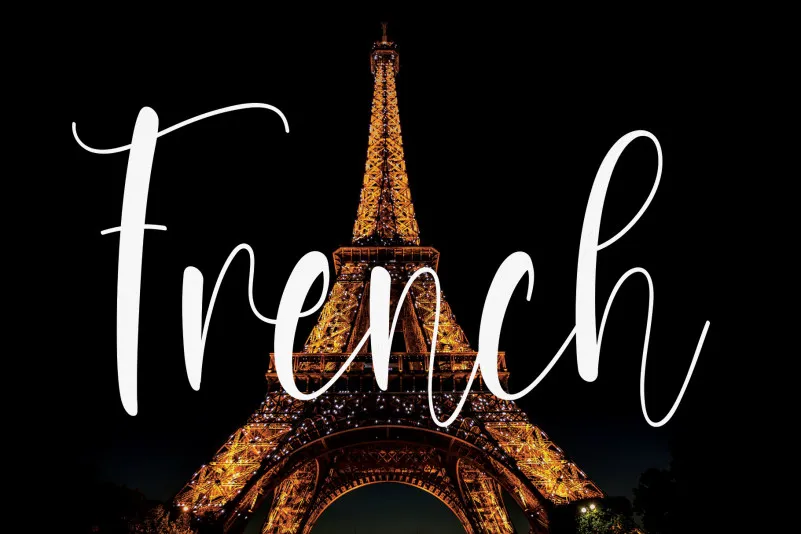
Farmwork Font – Download Grátis
Aqui está uma descrição em português para a página de download da font ‘Farmwork Font’, focando nas características do tipo de letra escrita à mão: Esta é uma fonte escrita à mão especial e criativa, com caracteres elegantes que impressionam com seu estilo! Use esta linda tipografia para adicionar um toque encantador a rótulos, designs de produtos, marcas d’água, fotografias e muito mais. Através da Farmwork Font, você pode enriquecer o design visual de qualquer projeto, tornando-o ainda mais único e sofisticado. Temos o privilégio de apresentar a fonte criada pelo designer creativeletter. Seja para dar um toque pessoal em uma embalagem ou transformar uma imagem em algo realmente especial, esta fonte escrita à mão garante que seu design seja inegavelmente atraente e memorável.